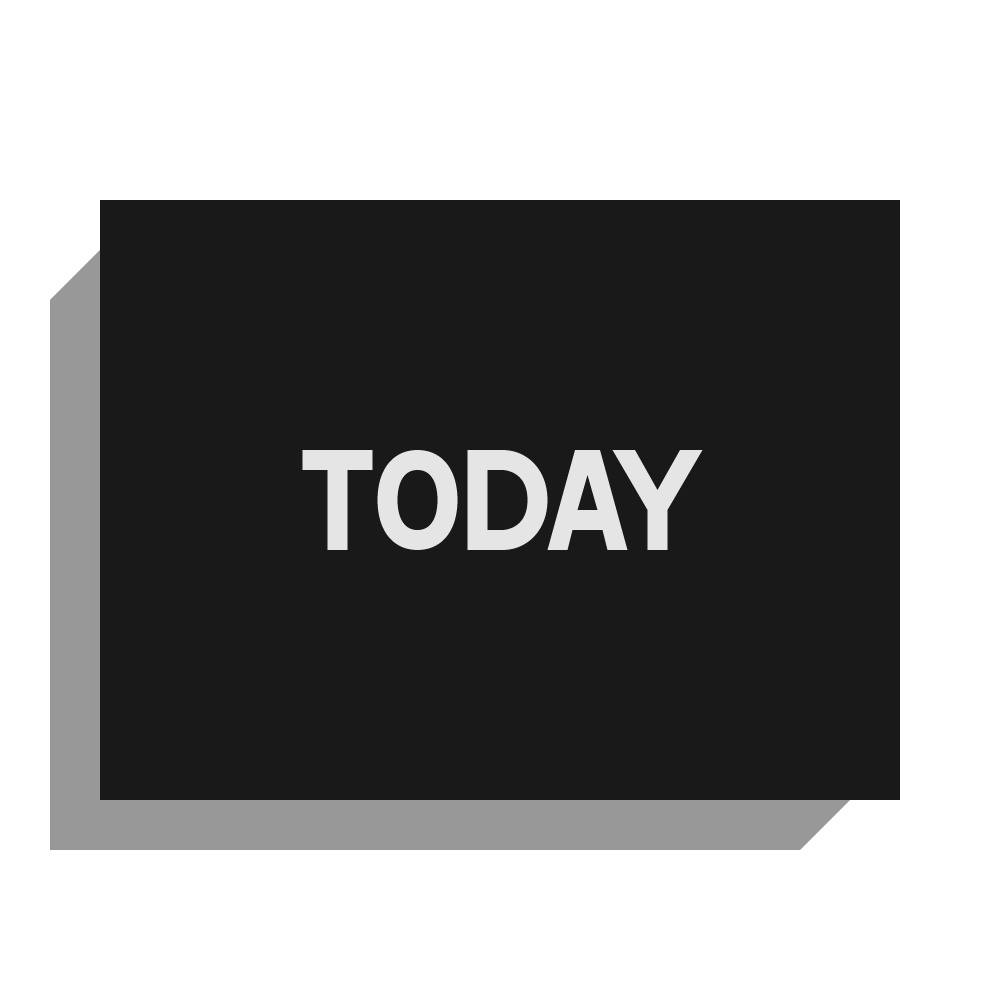
work space "khôra"フリーフォント 「TODAY」Digital0 JPYFree DownloadTODAY.zip (8.32 KB)TODAY.zipAbout Gift河原温のTODAYシリーズを参考に制作したOTFフォントです。 収録文字は大文字のアルファベット、数字、カンマとピリオドです。 ペアカーニングに対応しています。 このフォントはSIL Open Font Licenseです。work space "khôra"Visit FANBOX!Fontsフリーフォント 補助標識用数字書体「ほじょナンバー」work space "khôra"0 JPY